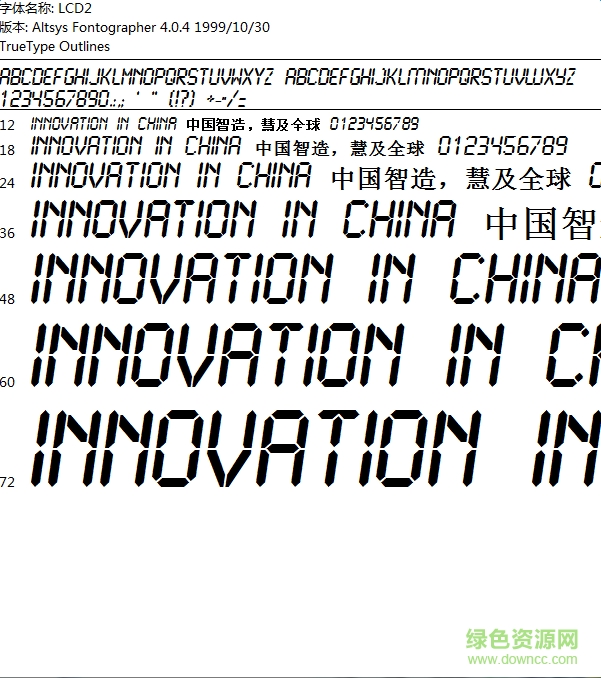
lcdlcdmono
lcdlcdmono字體是一款非常好看的英文字體軟件,筆畫類似于時鐘樣式,斷點相連,整體效果非常震撼,喜歡就到綠色資源網(wǎng)下載使用吧!
lcdlcdmono字體是一款應(yīng)用于藝術(shù)設(shè)計方面的簡體英文字體,該字體筆畫特色有創(chuàng)意,細(xì)節(jié)表現(xiàn)完整,且字庫完整,可以廣泛應(yīng)用于名片設(shè)計、新聞媒體、宣傳海報、ppt、影視制作以及內(nèi)容用字等領(lǐng)域。